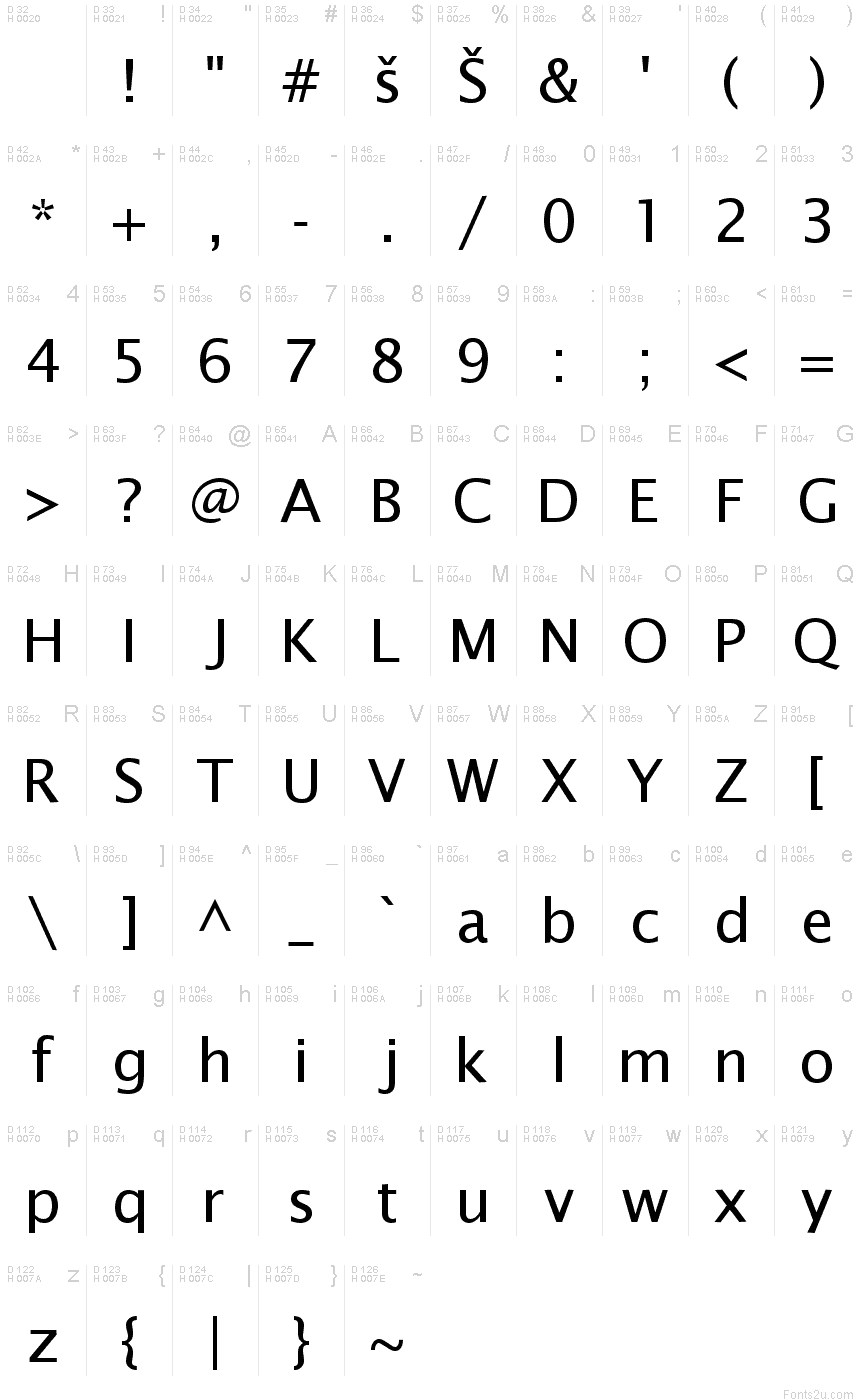
Nippur Sans to darmowy, neo-groteskowy krój bezszeryfowy od Bigelow & Holmes, który niesie ze sobą ducha szczerego modernizmu wczesnych lat 90. Litery są oszczędne i spokojne: proste kreski, krągłe kształty, zdecydowany pionowy rytm i wystarczająca miękkość krzywizn, by zwykły krój nie wydawał się chłodny.
Sprawdzi się w systemach identyfikacji wizualnej, podtytułach, etykietach interfejsów, opakowaniach i systemach informacji wizualnej, wszędzie tam, gdzie potrzebujesz neutralnego głosu z nutą ciepła. Jako darmowy font, dobrze sprawdza się też w tytułach, plakatach i krótkich logotypach, ponieważ kształty pozostają czyste i bezpośrednie, nie sprawiając wrażenia przesadnie „wykalkulowanych”.